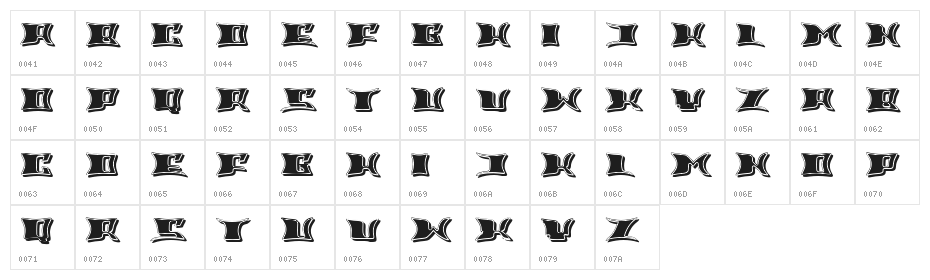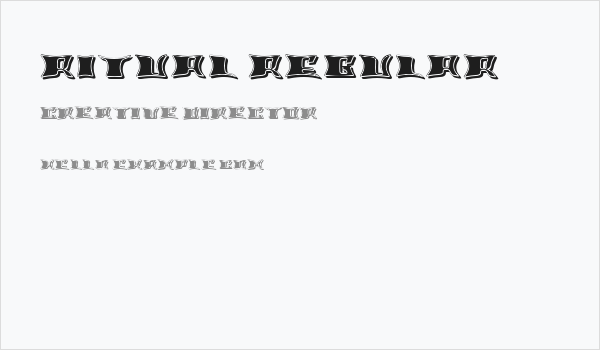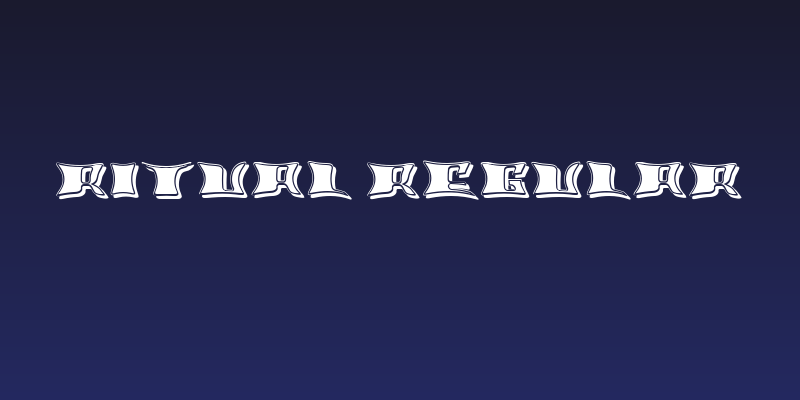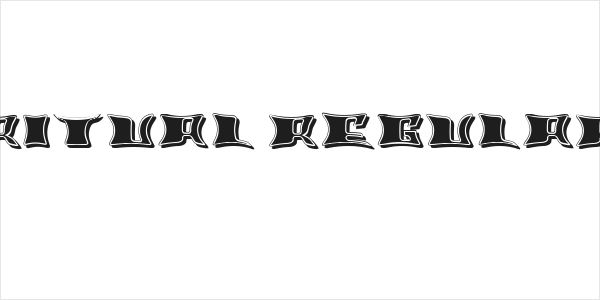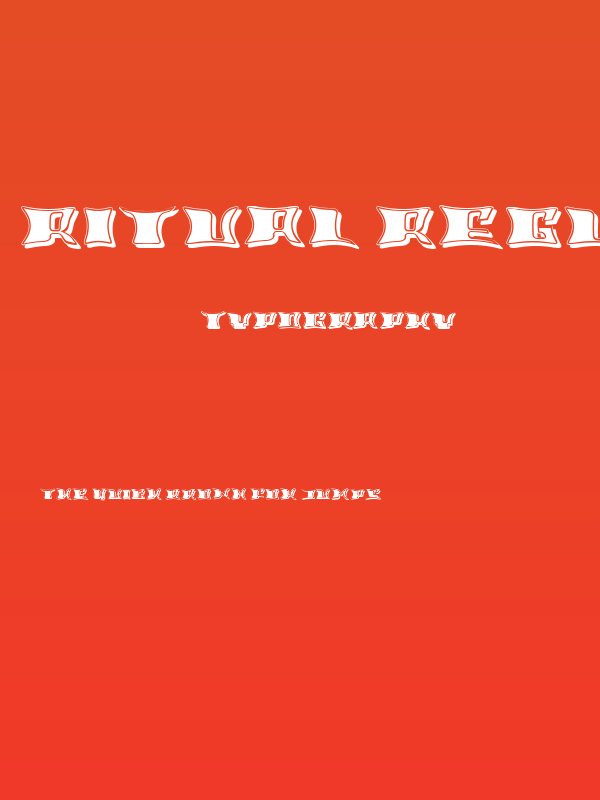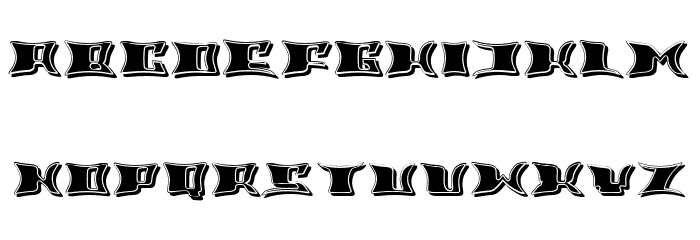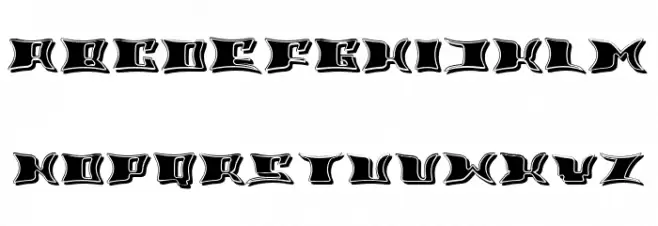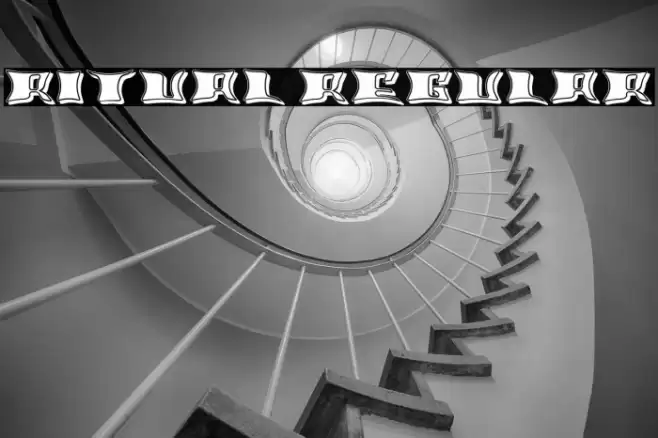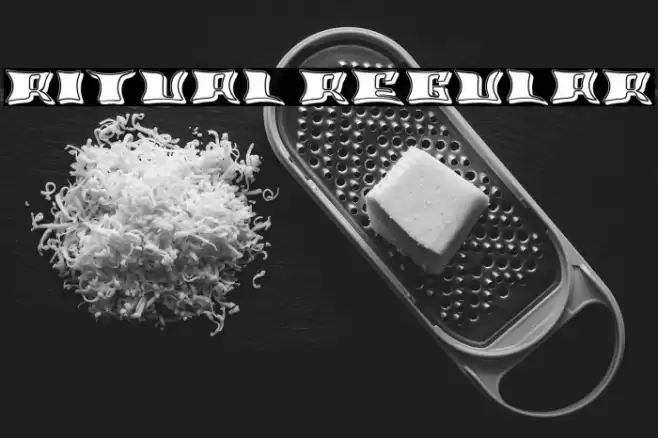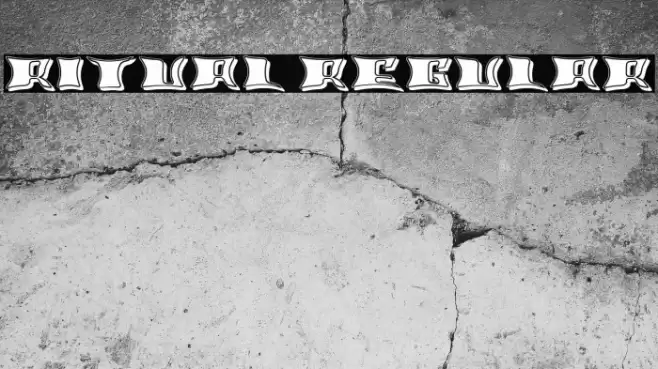
Ritual Regular Font
✎ Distorted Eroded
| Estilo geral | Vintage, Decorative |
| Projetos propostos | Ideal for use in branding, poster design, album covers, and any project requiring a dramatic and eye-catching typeface. |